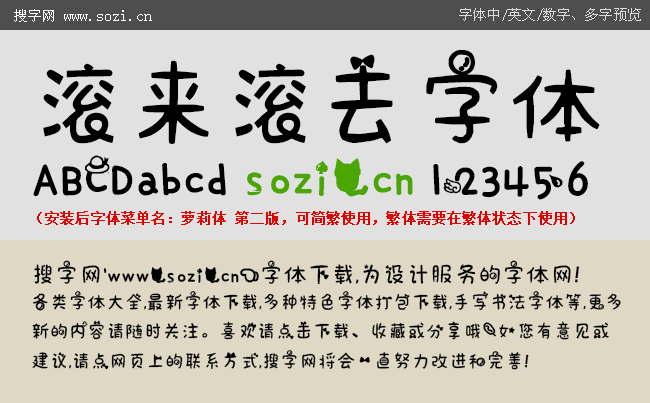
滾來滾去字體
搜字網(wǎng)給大家提供一款很有趣的手機(jī)中文字體下載。修改者給他起了個(gè)滾來滾去字體這么有意思的名字,這款手機(jī)字體是在字體筆畫間插入了可愛卡通圖案。趣味性實(shí)足,該手機(jī)字體個(gè)性實(shí)足,趣味性強(qiáng),又保持了文字的識(shí)別度,特別適合喜歡手機(jī)字體個(gè)性一些的朋友在手機(jī)上安裝使用。